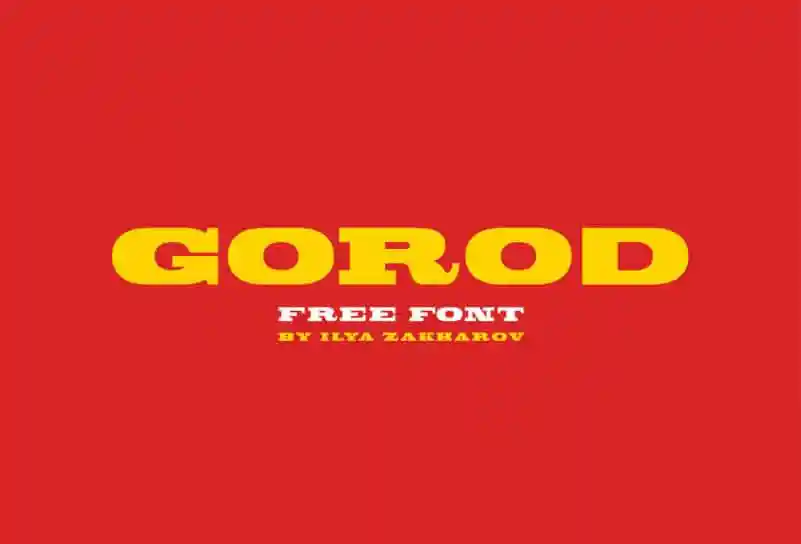
Gorod Slab Serif Font – Download Grátis
Agora é a hora de escolher uma fonte que pode dar vida à sua identidade visual, especialmente se você estiver criando materiais para o público geral ou para ambientes digitais. A Gorod Slab Serif Font apresenta-se como uma elegante e sofisticada opção, projetada especificamente para usar em grandes tamanhos de texto e cabeçalhos, garantindo um equilíbrio perfeito entre força e elegância. Com o intuito de evitar as características rusticas encontradas nas antigas fontes do tipo Egyptienne, a Gorod Slab Serif mantém seu traço robusto, enquanto desenvolve uma alta proporção de elegância e legibilidade. Isso permite que você use essa fonte em diversos ambientes, desde impressões digitais até dispositivos móveis, garantindo um visual profissional em qualquer situação. Ideal para criar identidades visuais como logos, marcas, cartões, pôsteres ou embalagens de produtos, a Gorod Slab Serif está equipada com tudo o que você precisa. Seu design clean e elegante lhe permitirá desenvolver projetos incríveis, mantendo ao mesmo tempo uma grande consistência em seu trabalho. E para designers gráficos, a fonte é perfeita para complementar sua paleta de cores, oferecendo um contraste visual interessante que destacará suas criações.